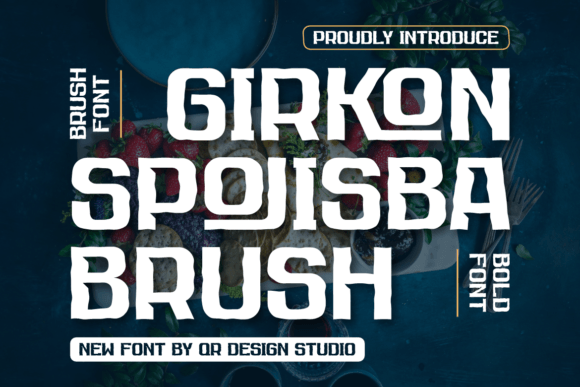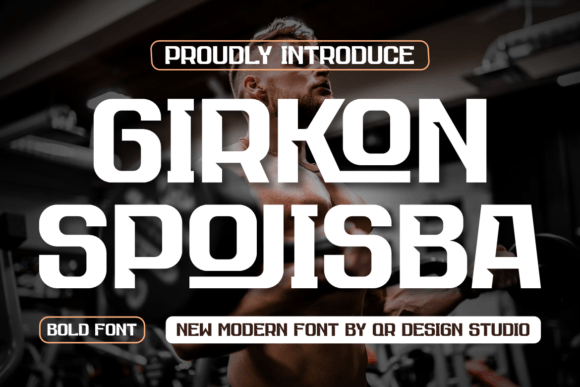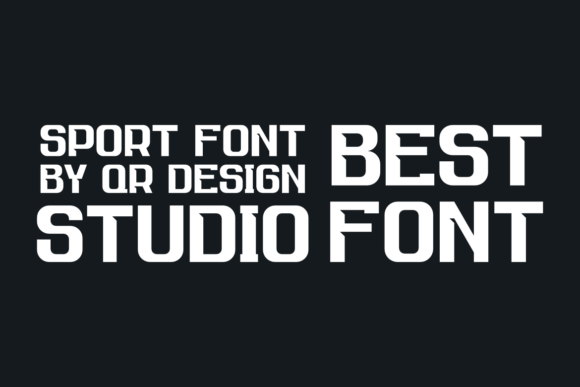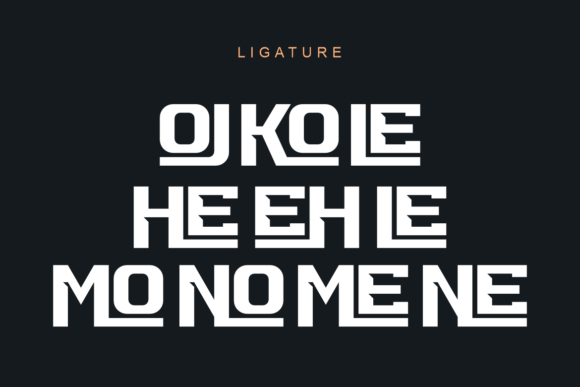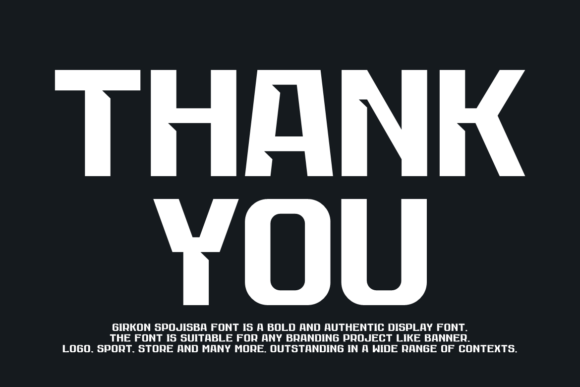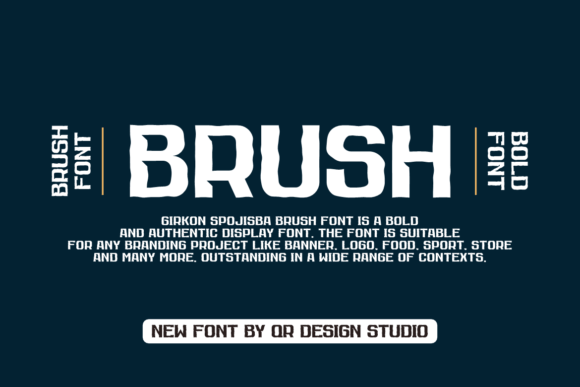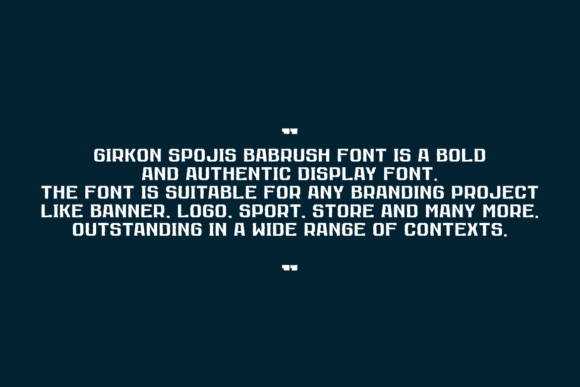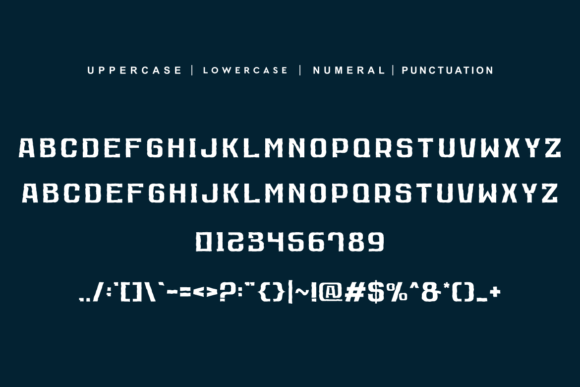
2 فونت Girkon Spojisba انگلیسی
دانلود مجموعه کامل فونت Girkon Spojisba انگلیسی Font گیرکان اسپاجزبا |
| ⭐ مجموعه فونت | دانلود فونت انگلیسی ترکیب ژیرکون Font Girkon Spojisba گیرکون سپاجیسبا براش Girkon Spojisba Brush |
| ⭐ توضیحات | فونت براش Girkon Spojisba یک فونت نمایشگر برجسته و معتبر است. این فونت برای هر پروژه برندسازی مانند لوگو، غذا، ورزش و بسیاری موارد دیگر مناسب است. برجسته در طیف گسترده ای از زمینه ها. |